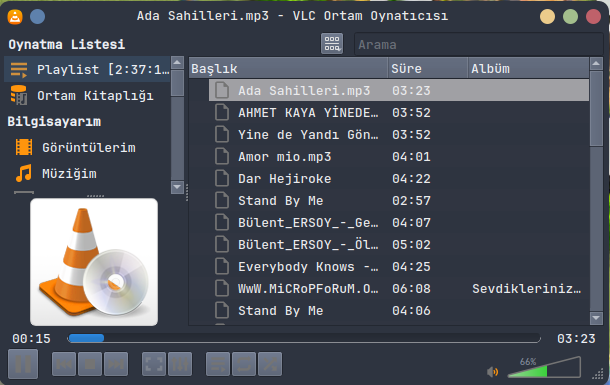
Türkçe destekli font önerileriniz
Karıştırırken şu fontu gördüm.. Sanırım ArchCraft'ın default tema fontu bu... İsmi de aklımda kalmadı ama gayet okunaklı .
Okunaklı da estetik 0 bence :p
Karıştırırken şu fontu gördüm. Sanırım ArchCraft'ın default tema fontu bu... İsmi de aklımda kalmadı ama gayet okunaklı.
Şu an estetiklikden daha çok görebilmeye odaklıyım. 🙃